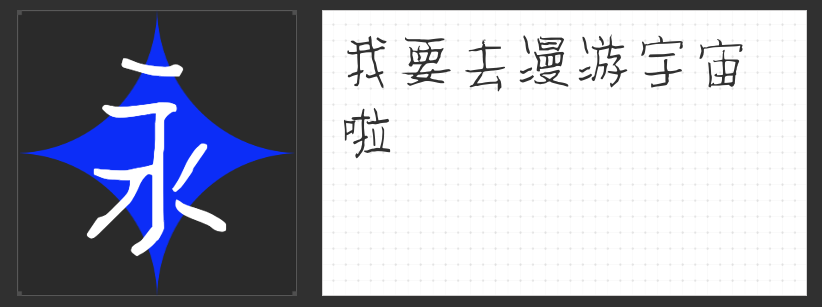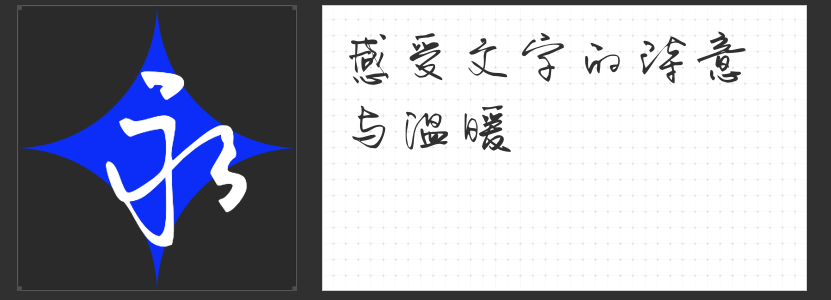
四款清新手写字体推荐:为设计注入诗意与温度
在设计中,手写字体常以独特的笔触与情感表达,赋予作品鲜活的生命力。若你正在寻找兼具清新气质与实用性的手写字体,不妨尝试以下四款风格各异的佳作,它们既能传递青春的灵动,也能承载自然的诗意,为视觉表达增添别样韵味。
1. 字青春青葱简 准粗
这款字体以“青春”为名,字形如少年执笔挥洒,既有随性不羁的笔触,又暗含结构上的平衡感。笔画粗细变化自然,墨色浓淡间透出纸张的肌理感,仿佛能闻到青草与书页交织的气息。它尤其适合用于校园主题海报、自然类文案或文艺书籍的标题设计,轻松营造出“岁月静好”的意境。
2. 小豆岛默陌纸鸢草书简
以“纸鸢”为灵感,这款草书字体将行云流水的连笔与舒展的笔画结合,中宫开阔的设计让文字在视觉上更具呼吸感。粗犷的笔画与流畅的转折形成反差,既保留了手写的温度,又提升了辨识度。无论是品牌故事中的抒情段落,还是旅游宣传中的诗意文案,它都能以独特的韵律感传递文字的温度。
3. MyFont濑户人鱼简
这款字体以低重心与不规则留白打破传统手写体的柔美印象,圆弧笔画被巧妙转化为折角,赋予文字几何化的现代感。方块状的字形结构既保留了手写的自然痕迹,又增强了排版时的稳定性。适用于需要平衡文艺感与现代感的场景,如艺术展览海报、独立杂志标题或社交媒体视觉设计。
4. 励字造仲夏简 常规
“仲夏”之名自带盛夏的热烈,而这款字体却以清秀的笔触与坚挺的钩画,诠释了传统与现代的融合。边缘斑驳的质感与洒脱的钩笔处理,让文字既有毛笔书写的筋骨,又不失现代设计的利落。其端正的字型与高通用性,使其成为商业海报、产品包装或短视频字幕的百搭之选,轻松驾驭从清新到活力的多元风格。
手写字体是情感与个性的载体,这四款作品或洒脱、或诗意、或现代、或传统,却都以“清新”为底色,为设计注入独特的温度。无论是传递青春的悸动,还是描绘自然的诗意,它们都能以笔触间的呼吸感,让文字真正“活”起来。